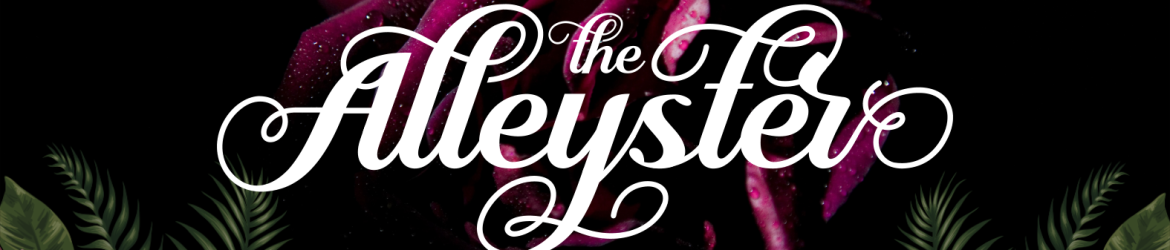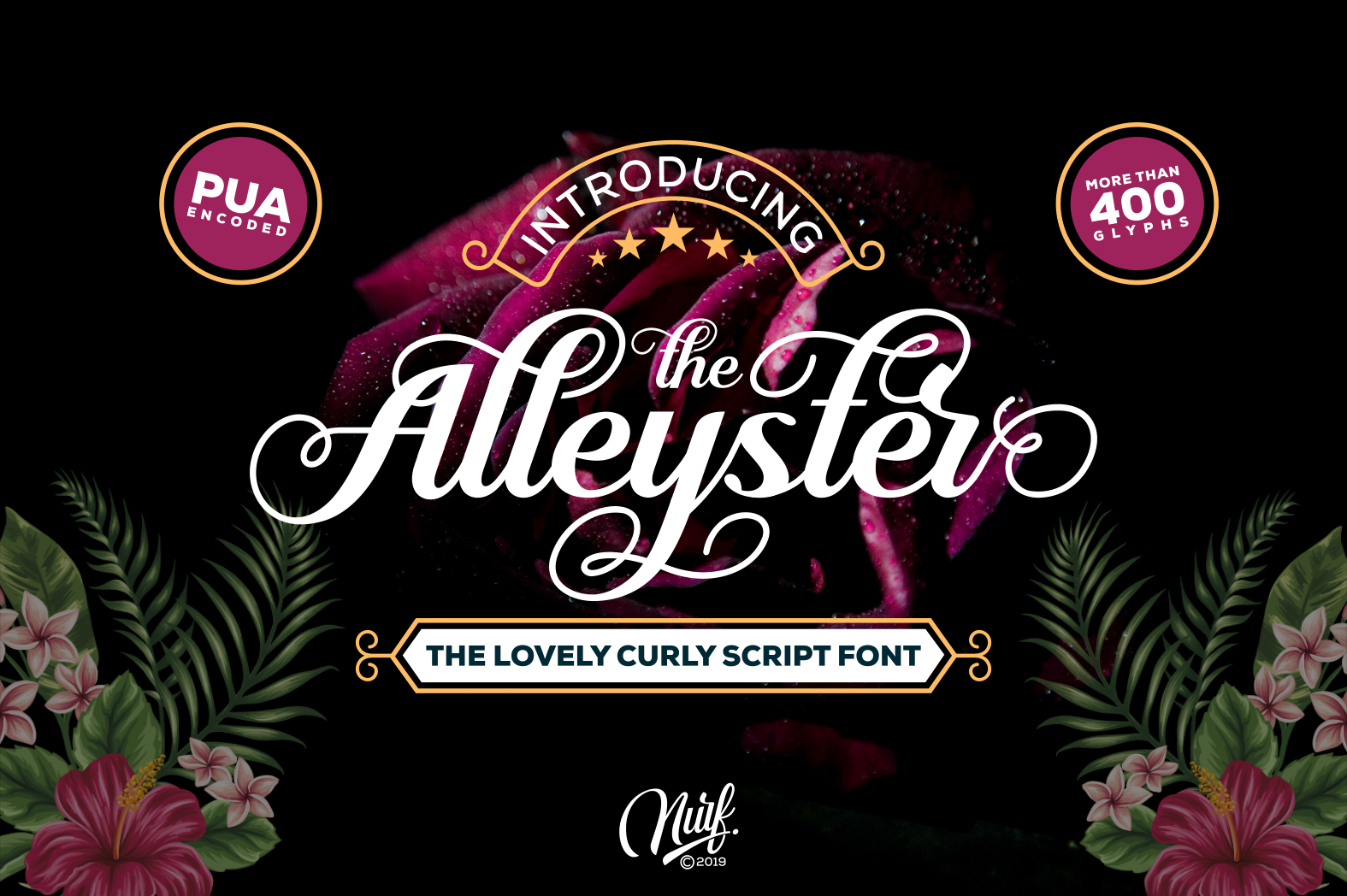
Alleyster Script Font – Fonte Grátis
Alleyster Script Font
A fonte Alleyster Script é uma delicada e curvilínea tipografia, ideal para projetos que buscam um toque moderno de escrita à mão. Com seu estilo de caligrafia moderna e seus caracteres escritos a mão incrivelmente detalhados, essa fonte se destaca como um ótimo escolha para criar logomarcas, posters, headlines ou qualquer outra aplicação gráfica que deseja destacar-se. Esta fonte traz uma personalidade única ao seu design, fazendo com que seus projetos apareçam ainda mais especializados e atraentes. Com Alleyster Script, você encontra um conjunto de recursos únicos para incorporar em suas criações, tornando-a o elemento perfeito para qualquer projeto visual que deseje se destacar.